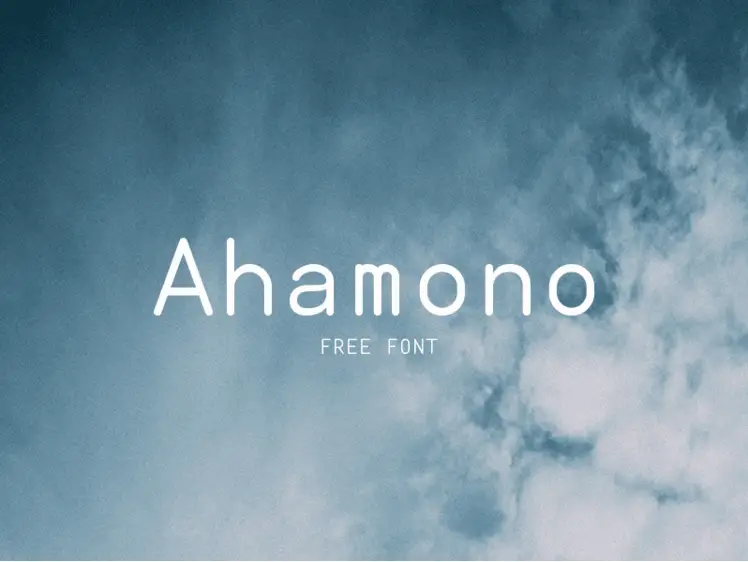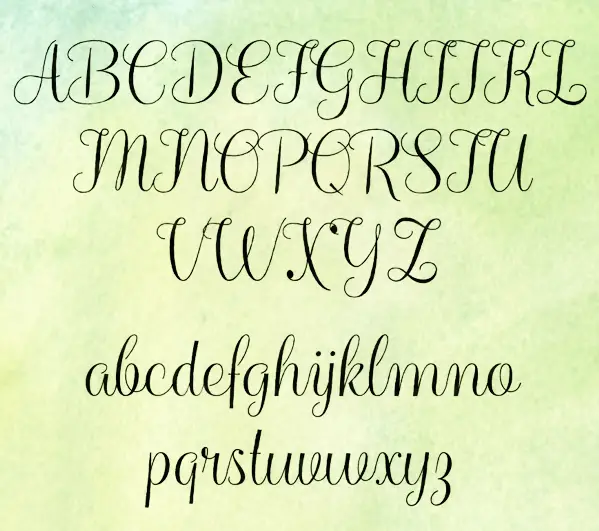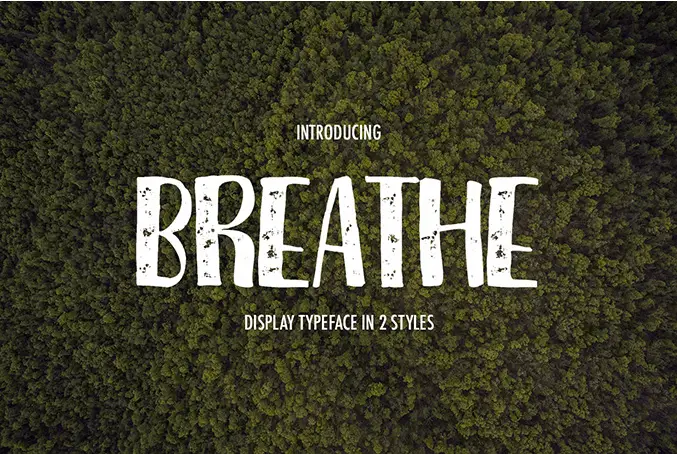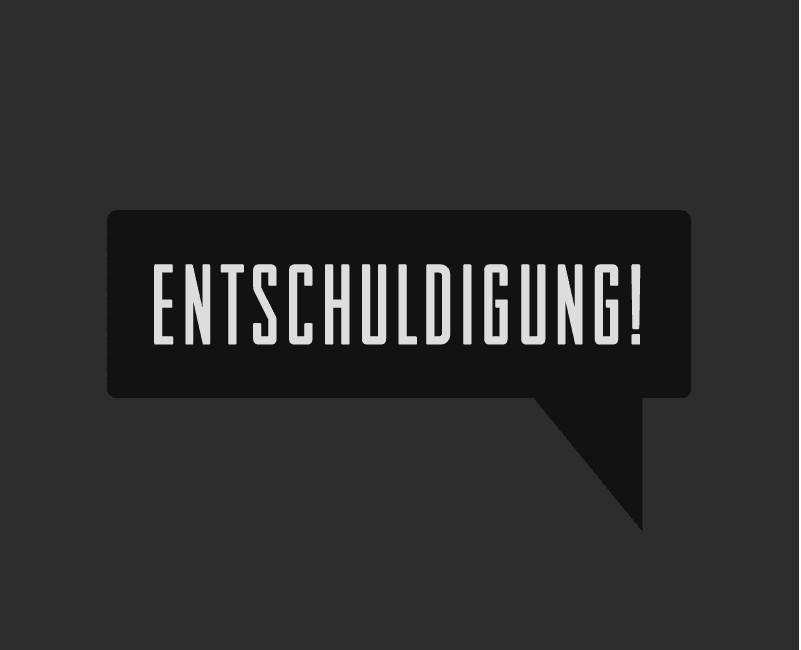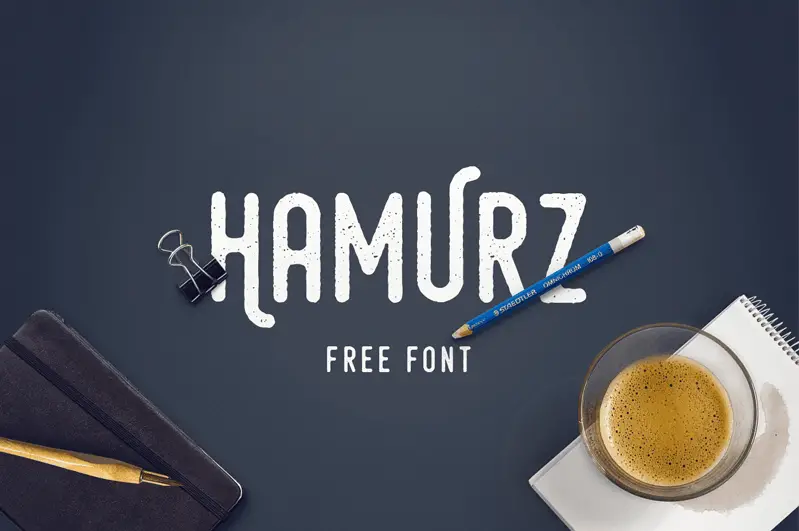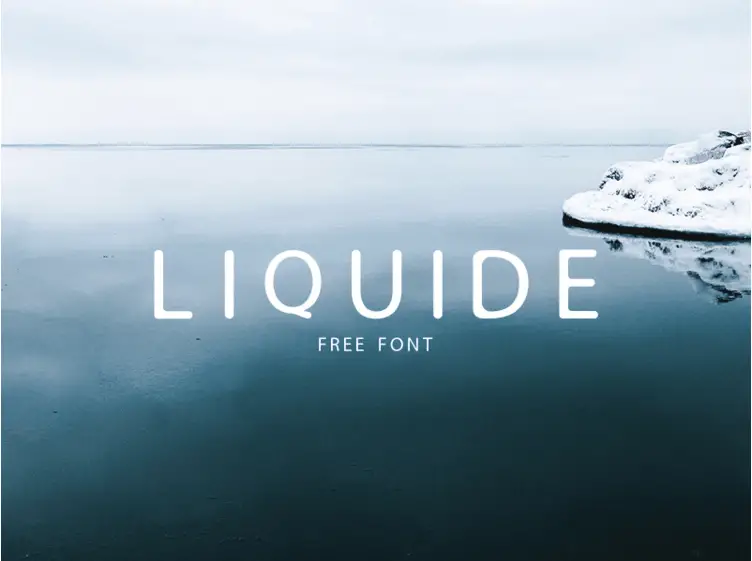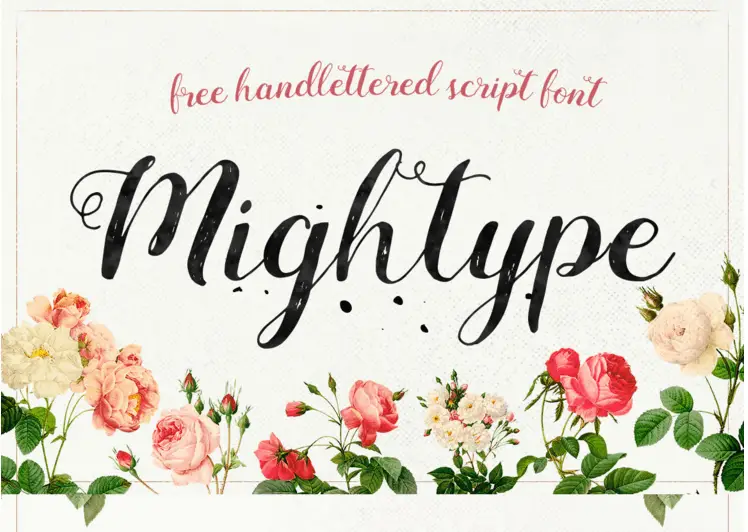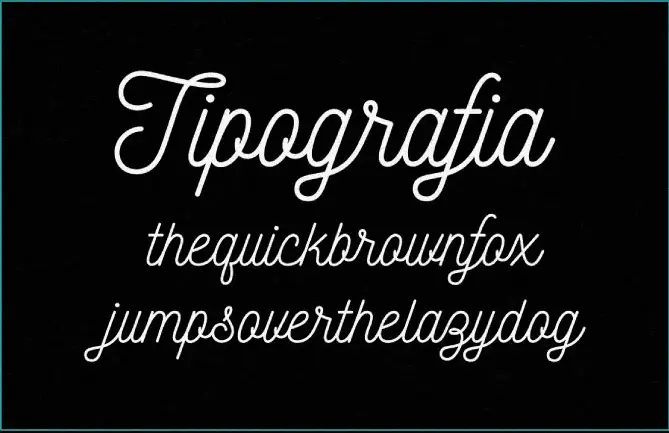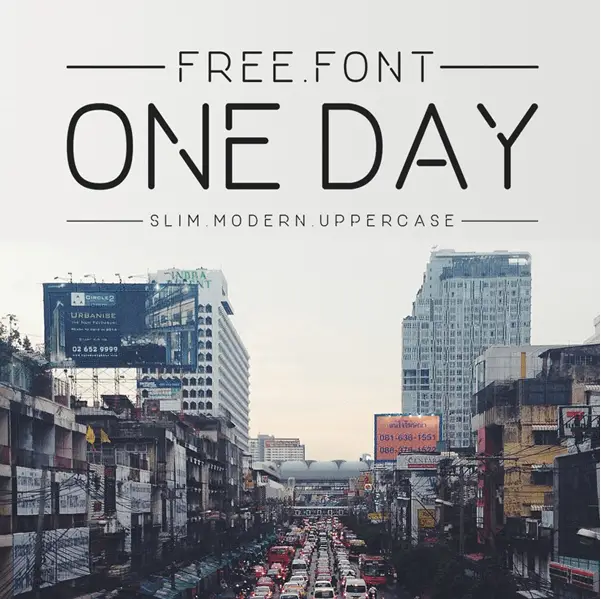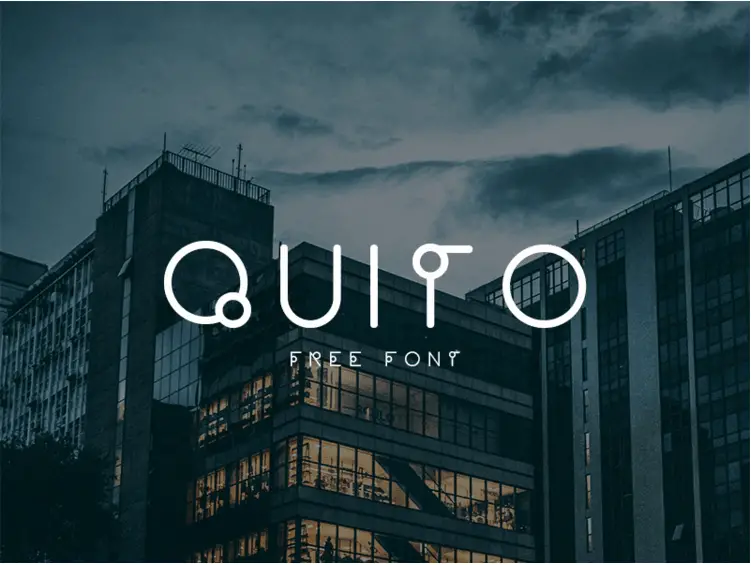
1. Mighttype-komentosarja
Mighttype-komentosarja
AF Studion tuoma sinulle rakkaudella, tämä upea käsinkirjoitettu fontti on itse asiassa osa premium-fonttipakettia, joka on tehty ilmaiseksi vain tätä varten sinulle suunnittelijoille. Pelaa kauneudellaan ja naisellisuudellaan seuraavaa suunnitteluprojektiasi varten.
2. Futuracha
futuristinen
Ripaus vintage-Egyptiä, joka melkein teleportoi sinut pyramidimytologioihin, on mitä ihailimme juuri tästä fontista. Ajatus ehdottaa, laitat sen suunnittelukoriisi ja käytät sitä runsaasti luovissa projekteissasi. Sen on jo ladannut yli 50,000 XNUMX ihmistä ja se on voittanut Evge-palkinnon. Veto, haluaisit käyttää sitä!
3. Yksi päivä
Eräänä päivänä
Tämä on tyylikäs isojen kirjainten taika, joka sopisi otsikoihin ja alaotsikoihin, kuten mikään muu puolimuotoinen …. puolirahallinen fontti. Luojat ovat sisällyttäneet isoja kirjaimia, numeroita ja merkkejä osana koko kirjasinpakettia. Voit vapaasti käyttää sitä ja jakaa rakkauden.
4. Hengittää
Hengitä fontti
Ja huokaa ihailua, kun olet hengittänyt kirjasinta tarpeeksi! Tämä kirjasinlaji on saatavana kahdella tyylillä, ja se on juuri sitä mitä tarvitset, jotta saat rauhallisuuden ja positiivisuuden suunnitteluympäristöön. Tartu se ja aloita kirjoitus!
5. Nickainley
Nickainley ilmainen fontti
Jos olet monoliini-komentosarjafani, tämä kiehtoo. Tämä kirjasin sisältää tyylikkyyden ja tyylikkyyden, ja se lisää omaa yksinkertaisuutensa ja suloisuutensa. Käytä sitä, pysy onnellisena! J
6. Balqis
Balqis
Rakastimme juuri tätä, ei kysymyksiä! Se on yksinkertainen, lupaa laajan näkyvyyden ja on kaunis katsella. Ja se on ilmaista! Mitä muuta voisit haluta ?!
7. Venetsia
Venetsian Serif-fontti
Tämä Serif on tyylikäs, nykyaikainen ja erittäin luettavissa – kolme ominaisuutta, joista jokainen suunnittelija vaihtaisi mehukkaimman makkaransa. Parasta on, että Unio Creative Studio on tehnyt sen ilmaiseksi kaupalliseen käyttöön.
8. Quito
Quito
Quito on melko epätavallinen fontti, jonka on kirjoittanut Fabian Korn. Se on mahtava valinta näytön kirjasimena. Olemme jo selvittäneet sen mahdollisen käytön laajuuden työpöydillämme. Sinun vuorosi nyt.
9. Hamurz
Hamurz-fontti
Tämä on yksinkertainen otsikkofontti. Ei paljon sanottavaa, toinen lisäys ilmaistarjouslistallemme ja suunnittelupakettiisi. Nauti rakkaudesta ja levitä sanaa!
10. Entschuldigung
Entschuldigung Fontti
Se on lievä teollisuuden kirjasintyyppi, joka sopii erinomaisesti rohkeisiin pienikokoisiin ja hipsterilogoihin. Lataa se ja aloita sen käyttö ilmaiseksi!
11. Jatko
Jatko-fontti
Sequel on monitoiminen kirjasintyyppi, tukeva ja hienostunut ulkonäöltään. Parasta tarjoustasi, kirjasintyypissä on jo sidoksia sanoille ‘ja’. Joten milloin tahansa kirjoitat “ja”, ne muuttuvat automaattisesti vastaaviksi ligatuureiksi. Viileä!
12. Yrsa ja Rasa
Yrsa Rasa
Nämä ovat 2 sisarfonttia, jotka on tuotu teille David Březinan ja Anna Giedryśin talosta. Kirjasinperhe tukee 92 kieltä latinankielisellä ja kahta kieltä gujarati-kirjoituksella. OK, emme käsittele niin paljon yksityiskohtia. Molemmat kirjasimet ovat mahtavia ja ansaitsevat komean osuuden ilmaisesta suunnittelukokoelmastasi.
13. Laiha
Laiha fontti
Tämä on yksi suosikeistamme … Muistutti meitä Ed Eddistä ja Eddystä. J Muistaa? Voit vapaasti käyttää sitä ja huvittaa asiakkaitasi sen yksinkertaisella viattomuudella.
14. Ahamono
Ahamono
Pyöristetty yksivärinen fontti, joka soveltuu käytettäväksi kuvissa ja omituisissa graafisen suunnittelun projekteissa. Luo kestävä vaikutus projektiisi sen tyylillä.
15. Neste
Nestemäinen
Nykyaikainen fontti yhdistettynä yksinkertaisuuteen! Rakastimme sen verkkokalvon ystävällisyyttä, sinäkin rakastat sitä !.